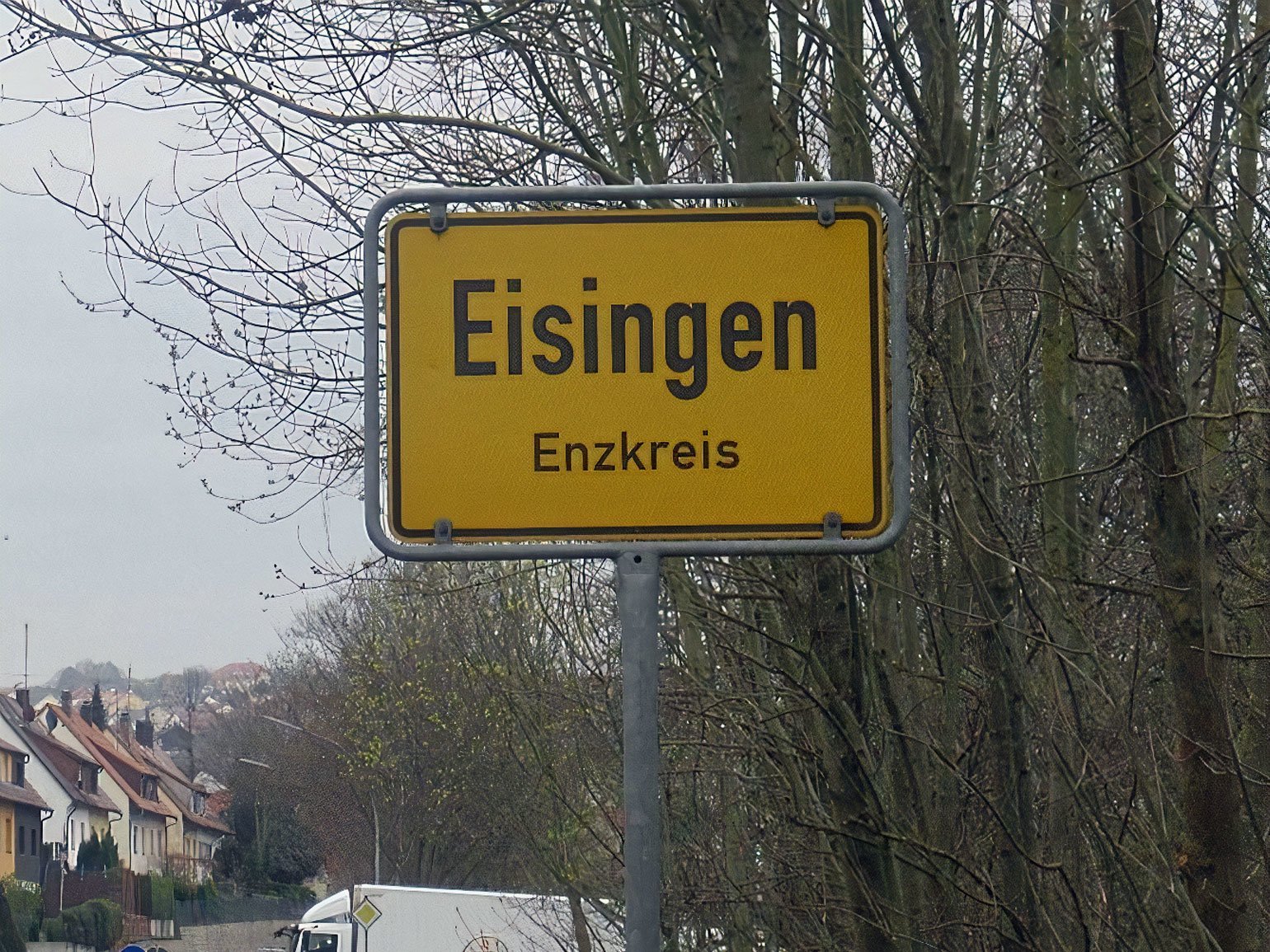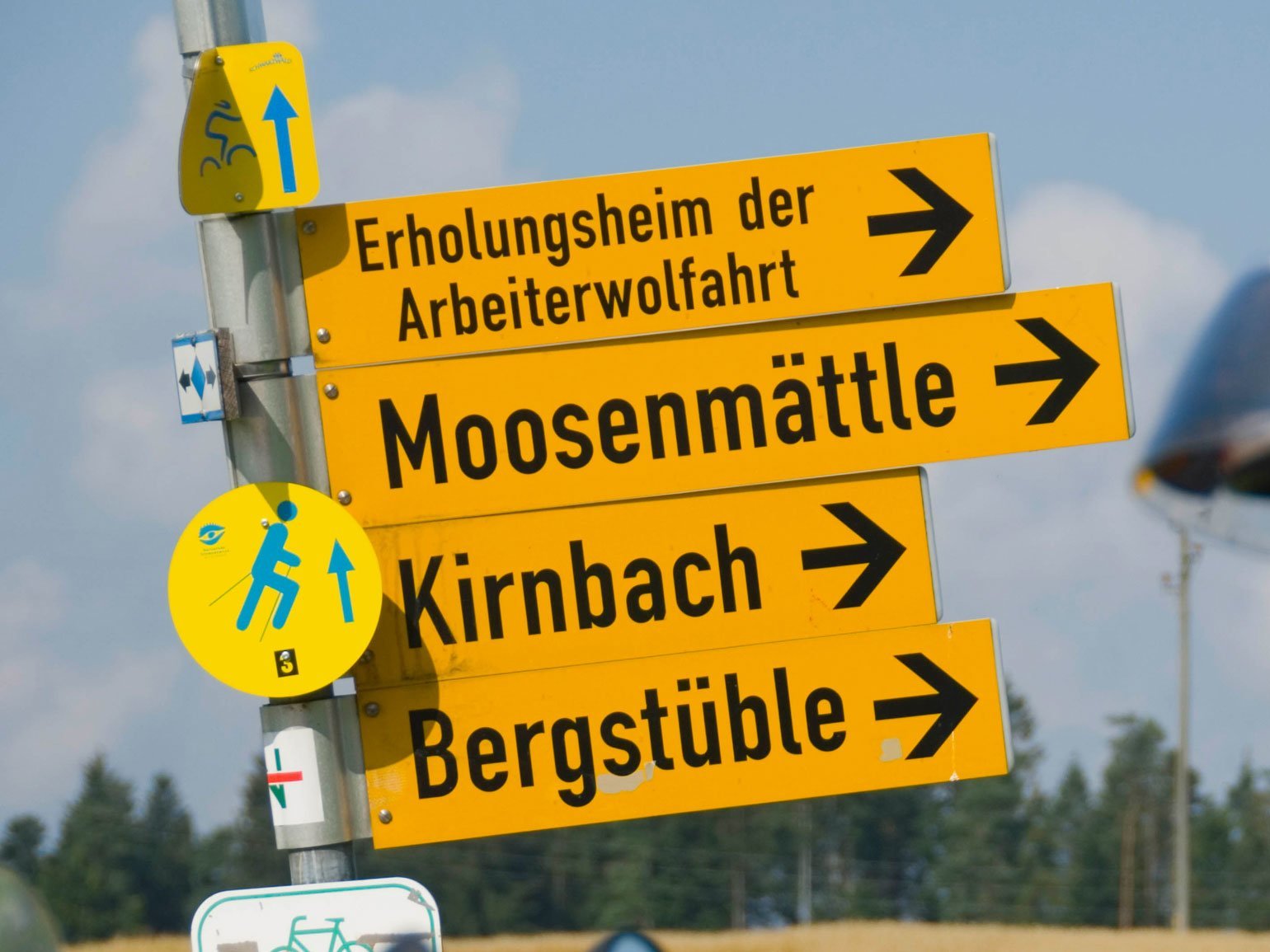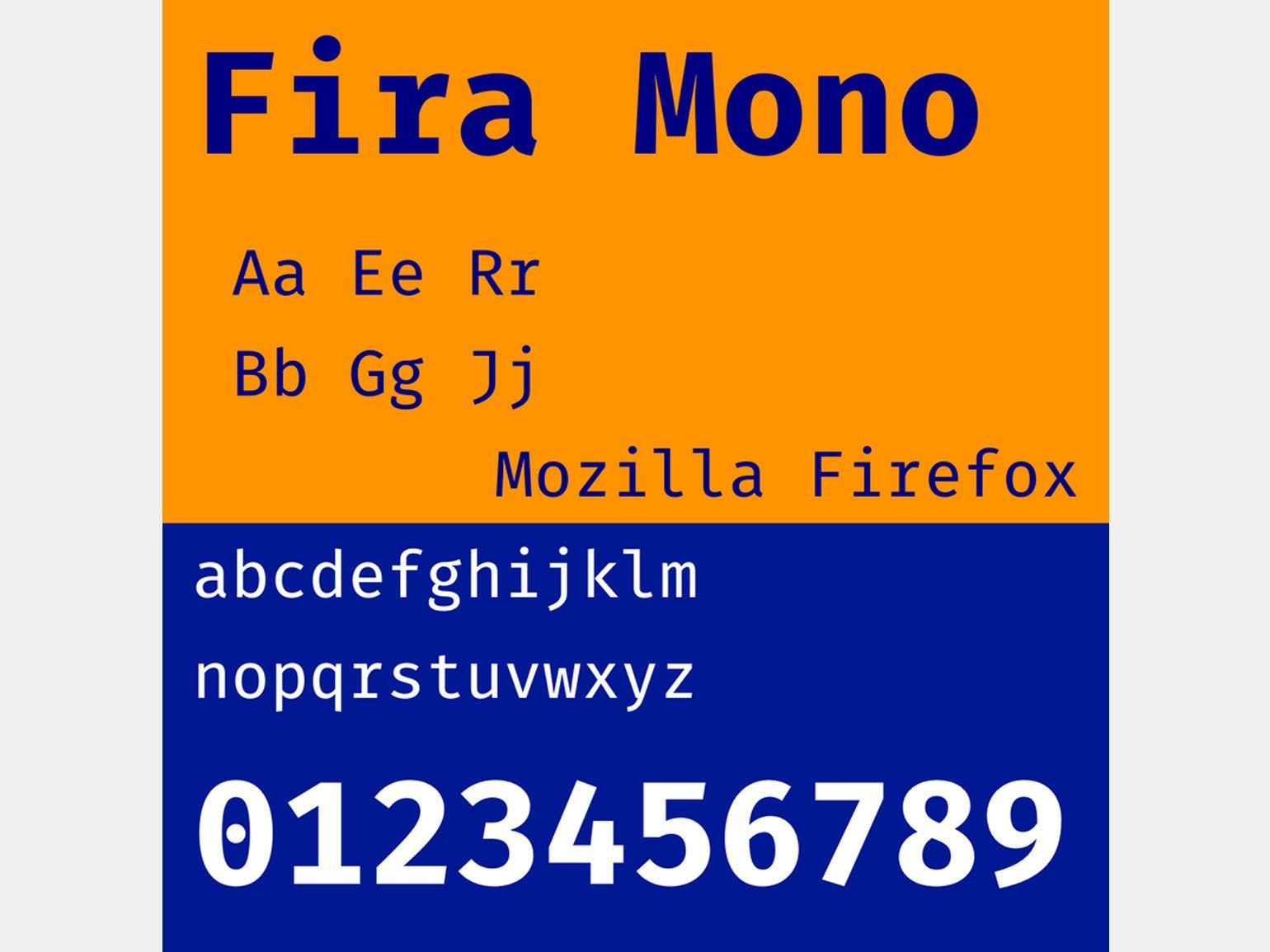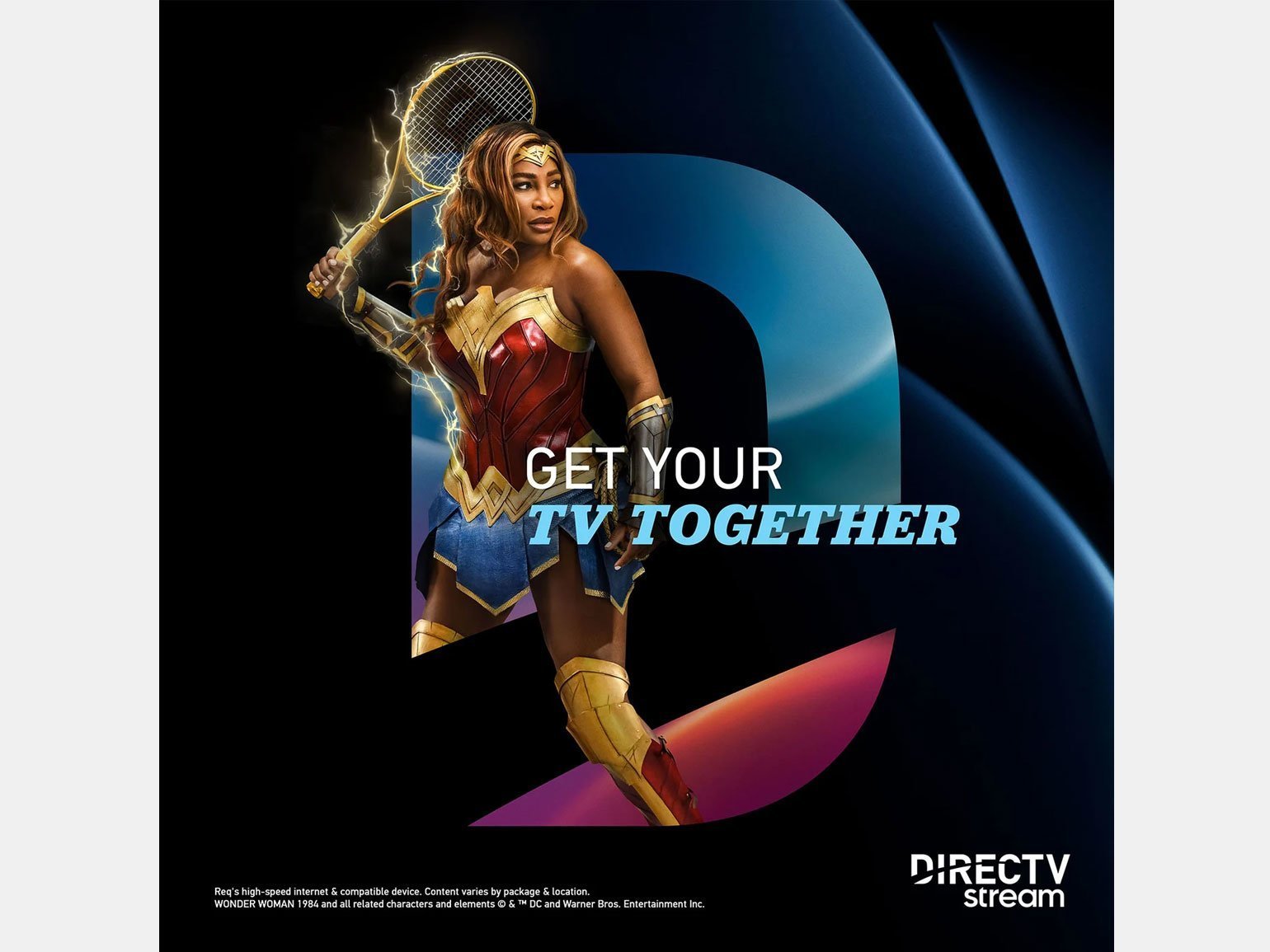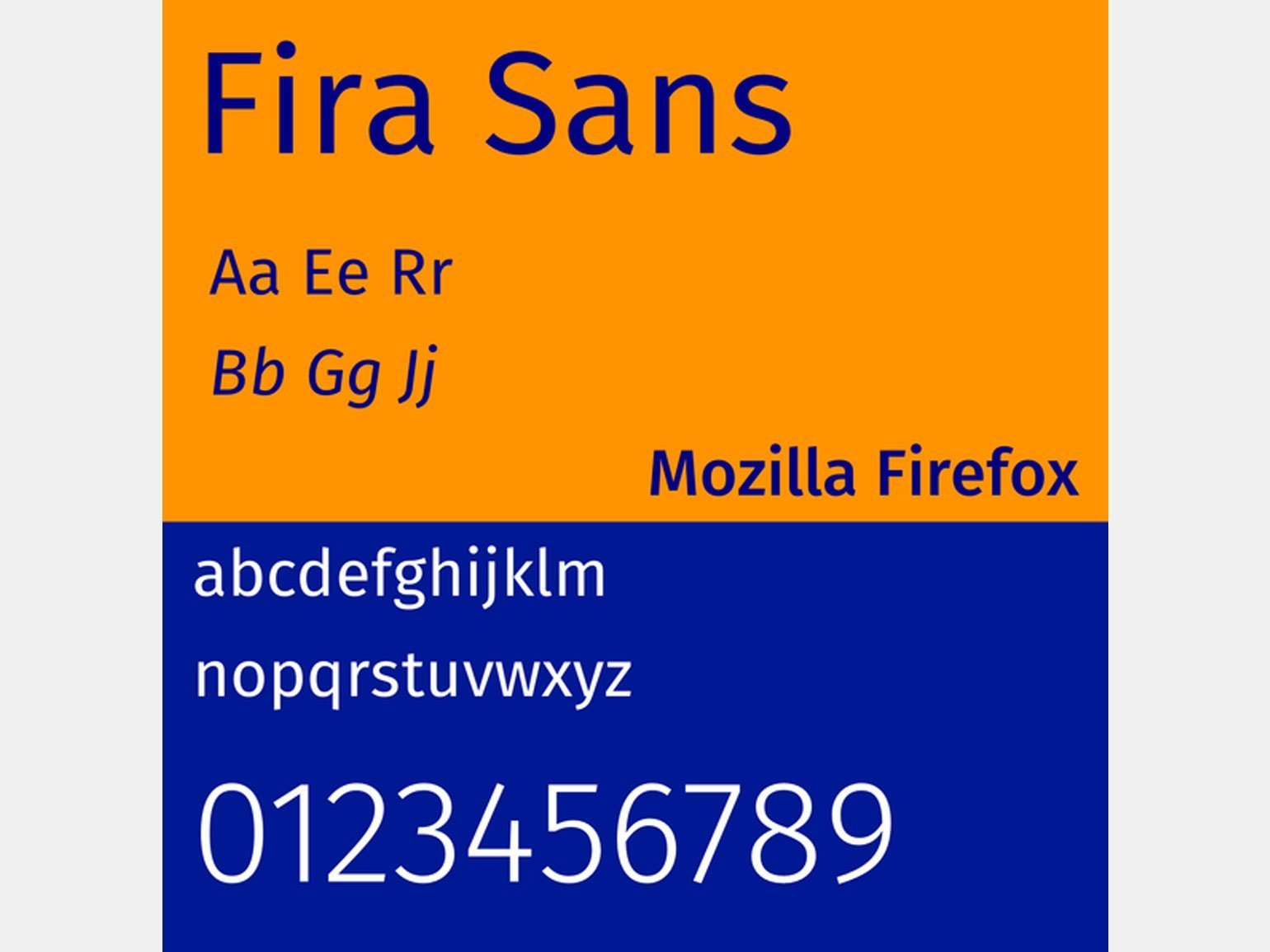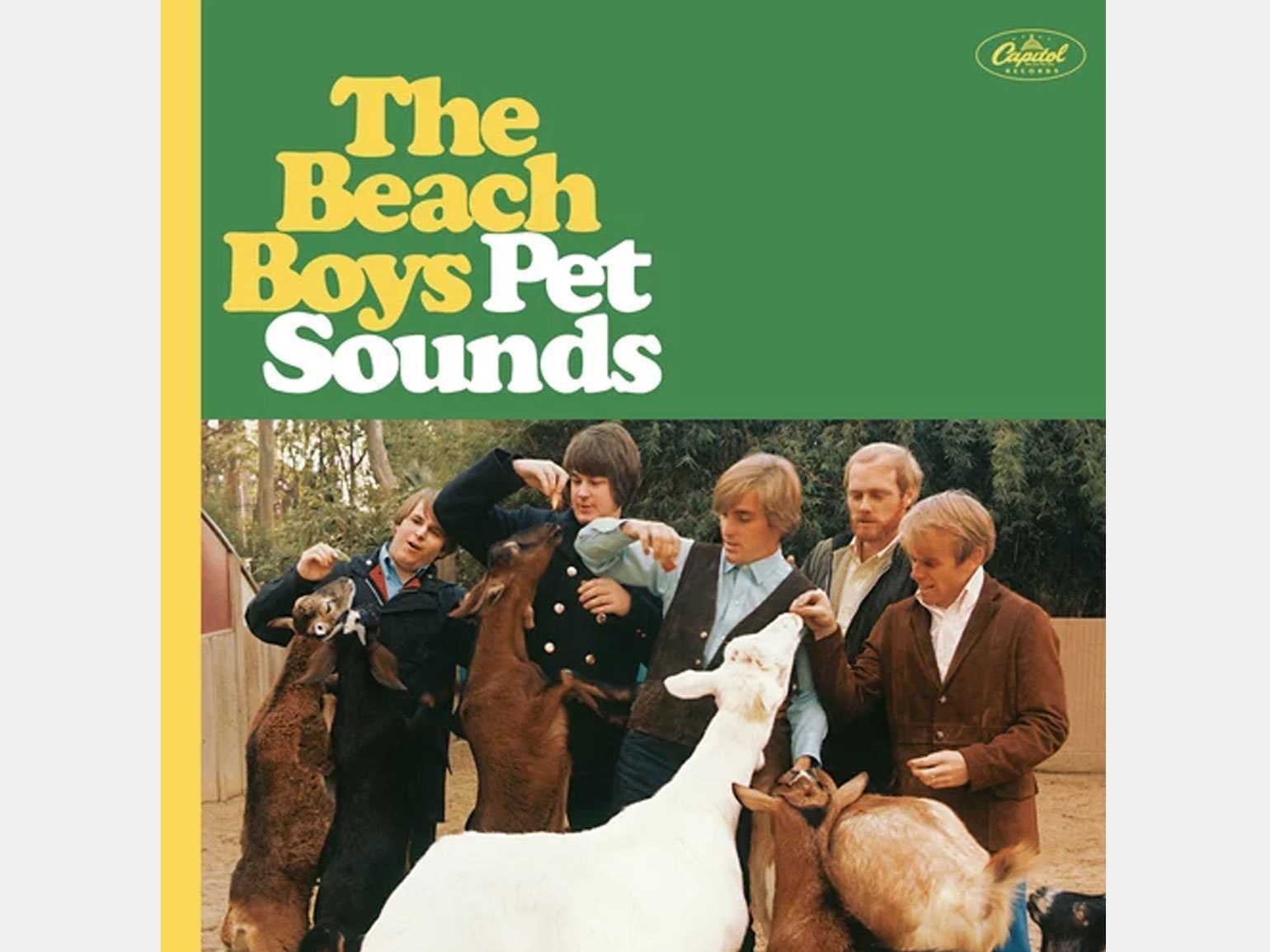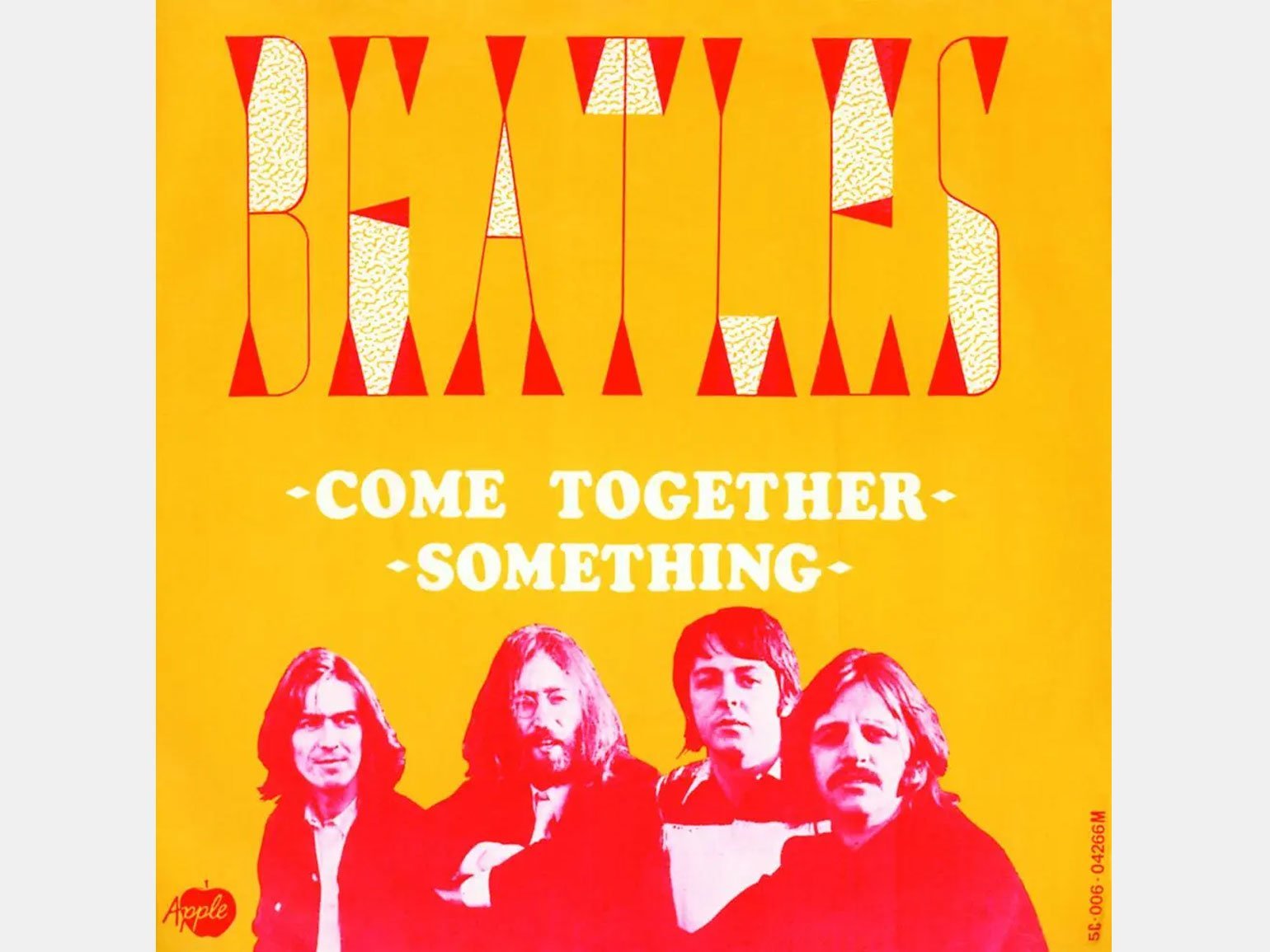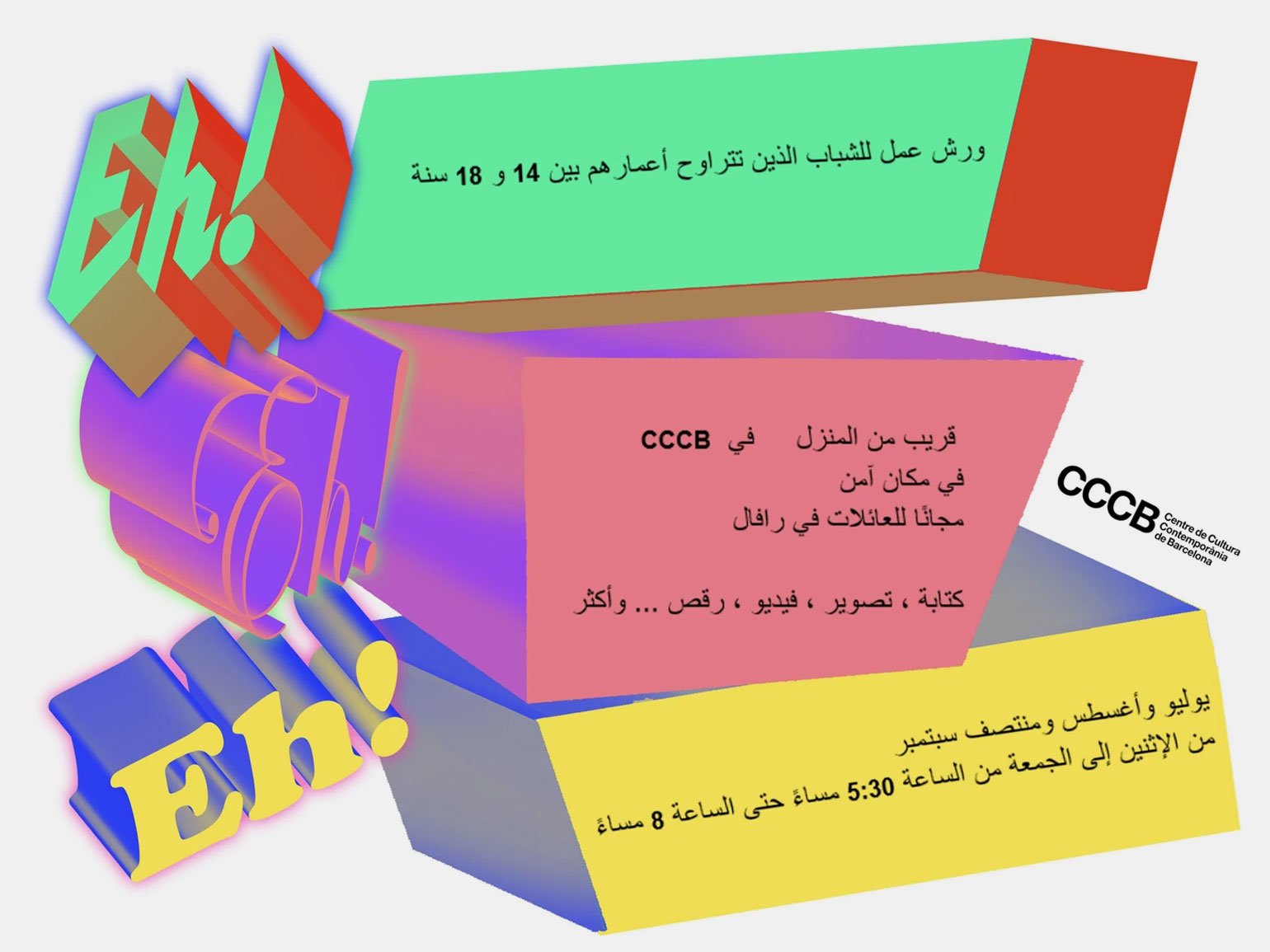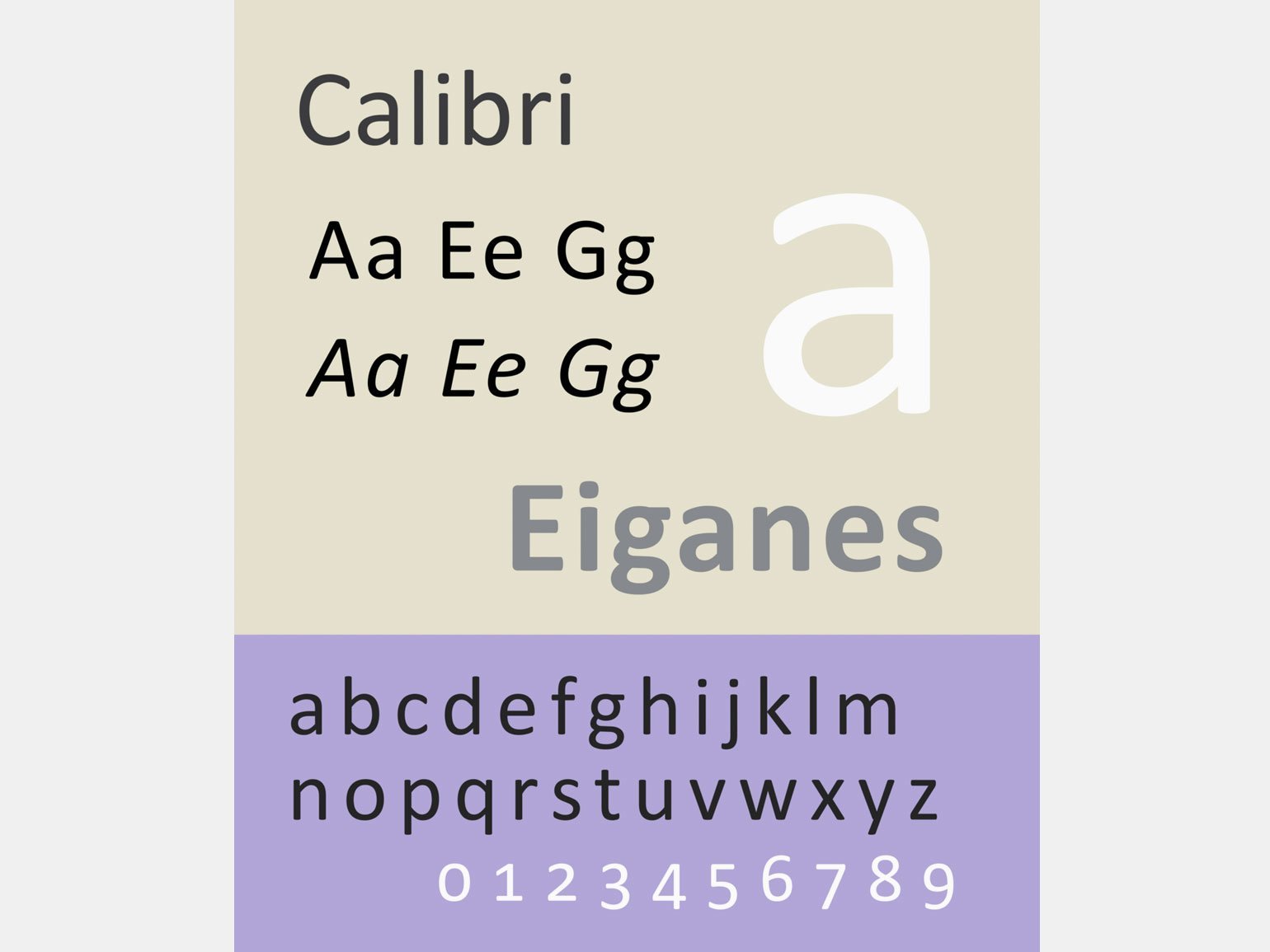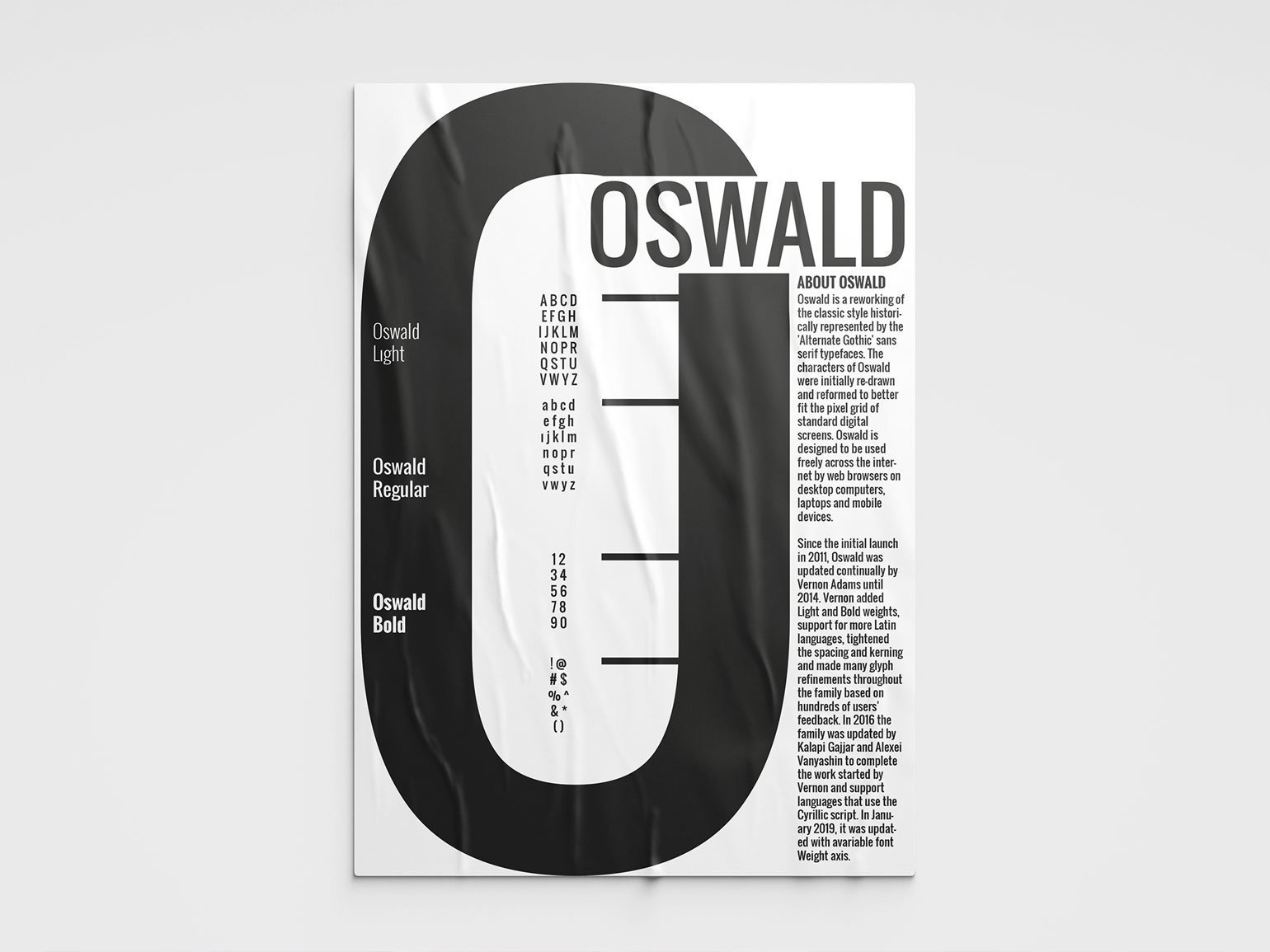
7 историй создания современных шрифтов
Каким был главный шрифт у рокеров 1960-х, как реставратор мебели работал с Google Fonts и какой символ Proxima Nova унаследовала из «Звёздных войн».
Как правило, дизайнеры рисуют шрифты, чтобы решить задачу продукта или бренда: показать ценности компании, добиться определённого настроения. Но бывает, что в результате работу автора используют не так, как он предполагал. Например, из шрифта для немецких грузовых вагонов получился DIN, а гарнитура Mozilla Firefox прижилась на правительственных сайтах.
Рассказываем, как дизайнеры придумали и сделали семь популярных шрифтов, которыми вы пользуетесь.
DIN
Это немецкий шрифт, который изначально был разработан для табличек на немецких железных дорогах.
История DIN начинается в 1905 году: похожие начертания букв были введены, чтобы унифицировать описания на грузовых вагонах. В 1920-м аналогичные надписи уже использовались для всех немецких поездов. А шрифт официально был выпущен в 1923 году — в типографской мастерской D. Stempel AG взяли за основу начертания для железных дорог и доработали их. Это была довольно крупная мастерская — в ней же, спустя несколько лет, создали ещё один широко известный шрифт — Memphis.
DIN — это аббревиатура от Deutsches Institut für Normung (Немецкий институт стандартизации). Первая гарнитура называлась DIN 1451. Со временем она распространилась по всей Германии: её использовали для дорожных знаков, нумерации домов и даже на упаковках потребительских товаров. В гарнитуре было два начертания: обычное (Mittelschrift) и condensed (Engschrift). В Германии их до сих пор можно встретить в городской навигации:
Указатель, напечатанный Engschrift
В 1995 году Альберт-Ян Пул провёл незначительный редизайн шрифта — так появился FF DIN, который и сейчас активно используют в рекламе и айдентике.
Логотип Sustane
Постер фестиваля d’Angoulême
В нулевых годах появились ещё версии. Одни из наиболее известных — DIN Next и PF DIN.
DIN Next в навигации Silesian Museum
PF DIN в рекламе DirecTV Stream
Fira Sans
Этот гуманистический гротеск разработали в 2013 году для Firefox OS от Mozilla Corporation. В том же году Fira выложили в свободный доступ. Над гарнитурой трудился известный шрифтовик Эрик Шпикерманн совместно с командой студии Carrois Type Design.
Помимо Fira Sans c несколькими начертаниями, была разработана моноширинная гарнитура — Fira Mono.
Сейчас Fira Sans — официальный шрифт Правительства Новой Зеландии, а также его используют в отдельных веб-ресурсах госструктур США и Канады.
Fira Sans использован для навигации и основного текста
Fira Sans использован для основного текста
Cooper Black
Это жирный контрастный шрифт без единого острого угла: его выпустили в 1922 году и назвали в честь создателя — дизайнера Освальда Брюса Купера.
Cooper Black возник как переработка Cooper Old Style — похожего шрифта с более тонкими буквами, который Купер выпустил в 1919 году. Общественное признание шрифт приобрёл после смерти автора — в 1960-х годах, с ростом популярности поп‑арта. Его часто использовали дизайнеры музыкальных обложек. Например, в 1966 году Cooper Black использовали The Beach Boys, позднее — The Doors, Дэвид Боуи, The Beatles.
Популярность Cooper Black продолжалась и в 1970-х: его по-прежнему использовали для оформления музыкальных дисков, а также для рекламы и логотипов
Логотип тележурнала 1976 года
В наши дни Сooper Black продолжают использовать — хоть и не так активно.
Реклама бренда здорового питания
Реклама воркшопов в Монако (Cooper Black использован в левом нижнем углу)
Calibri
Calibri до недавнего времени был главным шрифтом Microsoft. Его автор — голландский шрифтовой дизайнер Лукас де Гроот.
К началу нулевых де Гроот уже успел стать известным в профессиональных кругах и занимался собственной шрифтовой студией LucasFonts, а работу для Microsoft ему предложили через посредника. Ключевым требованием было удобство чтения с экрана.
Разные начертания Montserrat на упаковке The Really Nice Sauce Co.